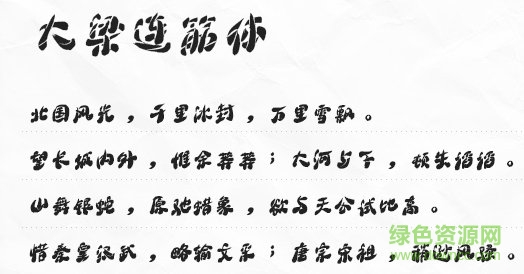
大梁連筋體是一款根據(jù)大梁體為模板創(chuàng)作的連筋字體,整體造型看似間斷實(shí)則連貫流暢,給人端正嚴(yán)明的視覺體驗(yàn),歡迎大家來綠色資源網(wǎng)下載使用!
大梁連筋體采用了大梁字庫(kù)的書法字體模板,延續(xù)了古代中文字體的文風(fēng)和造型,適合大標(biāo)題藝術(shù)和廣告設(shè)計(jì)的字體!
大梁體筆鋒犀利,字形大氣磅礴,整體效果非常出眾!
連筋字體是一類用于鏤空,噴漆效果設(shè)計(jì)方面的字體。